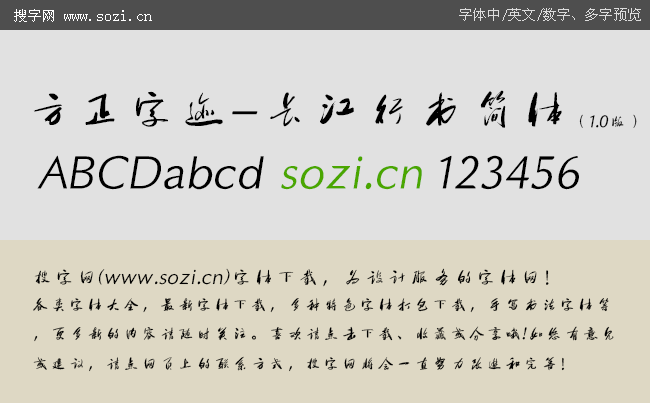
方正字跡-長江行書簡體
搜字網(wǎng)提供一款方正字跡-長江行書簡體中文字體下載,方正字跡-長江行書簡體是一款中文手寫書法字體,字體書寫流暢自然,整體效果瀟灑大方,非常出色。適合應(yīng)用于廣告設(shè)計(jì)、海報(bào)設(shè)計(jì)、包裝印刷、產(chǎn)品設(shè)計(jì)等應(yīng)用。